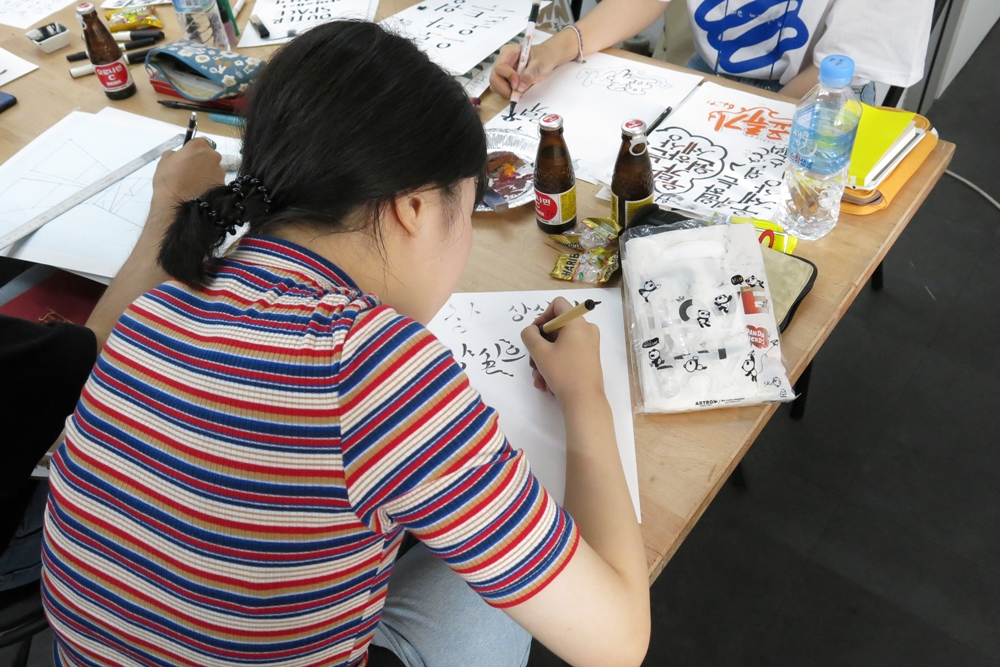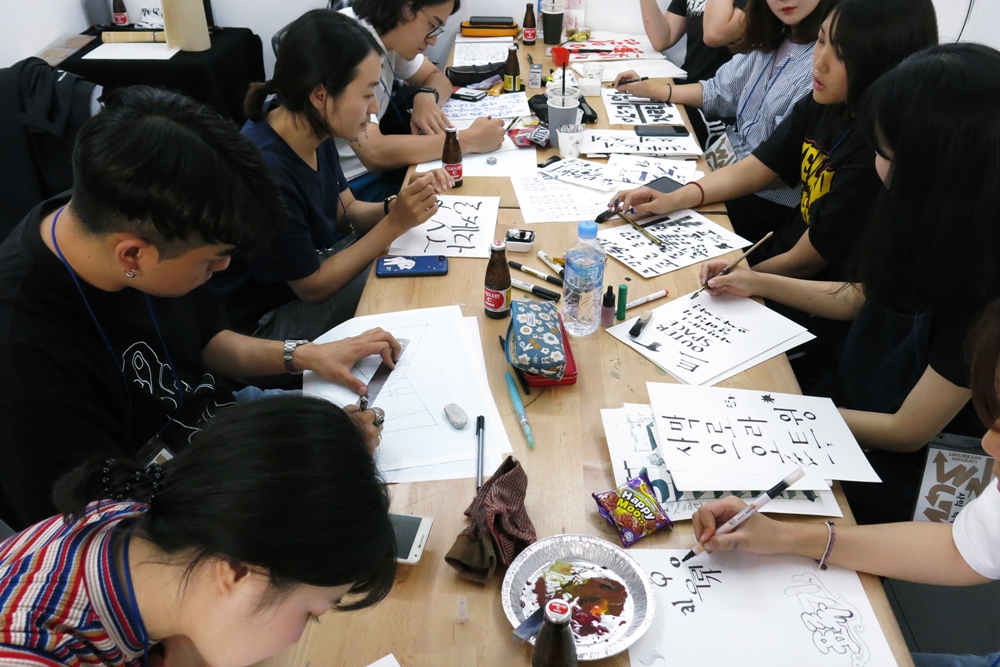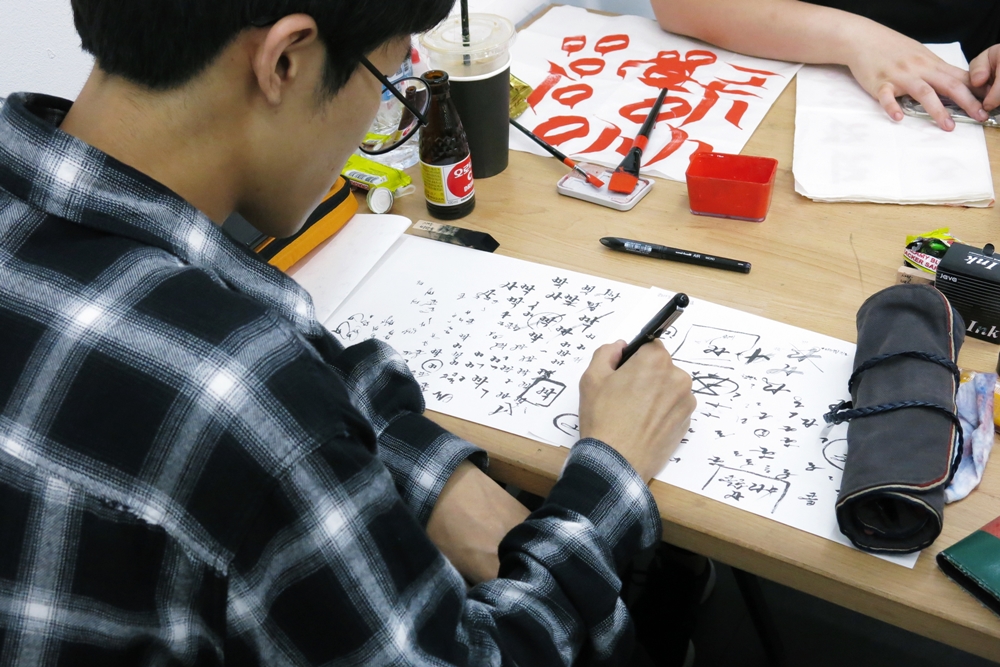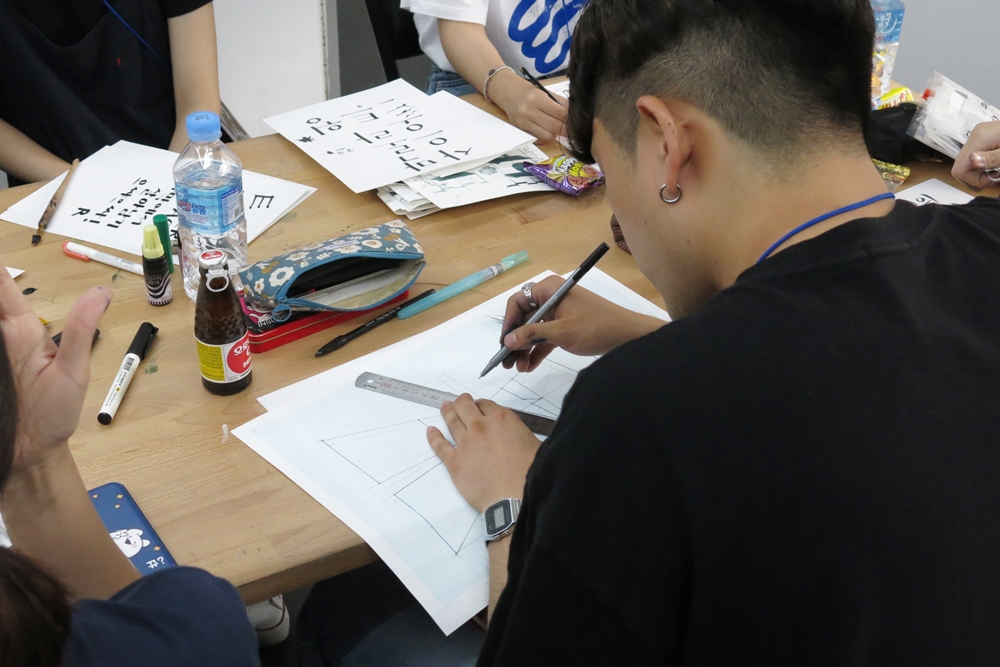
표류된 디자이너들의 탈출기, <디자인캠프2018, 우정국 표류기>를 다녀와서
<우정국 표류기>.
처음 캠프의 주제를 보았을 때, 의아했다. ‘우정국은 무엇이고 디자이너들이 왜 표류를 하지?’
태풍 솔릭이 서울에 상륙하던 날, 의문을 해소하기 위해 표류의 현장을 찾았다. 올해로 4회째 맞은 디자인학교의 디자인캠프는 8월 22일부터 26일까지 4박 5일 동안 진행되었다. 상수역과 광흥창역 중간에 위치한 캠프 장소는 길을 잘못 들어섰나 싶을 정도로 의외의 곳에 있었다. 주택가들 사이에 덩그러니 위치한 건물의 외관은 오래된 동주민센터 같았다.
알고 보니 디자인캠프가 열린 ‘탈영역 우정국’은 실제로 창전동 우체국이었던 장소를 탈바꿈한 곳이었다. 우정국은 우체국의 옛말이며, 업무공간으로 쓰이던 1층과 관사로 쓰이던 2층이 모두 새로운 문화공간으로 활용되고 있었다.
안으로 들어서자 6~7명 정도 모인 디자이너들이 노트북으로 작업을 하면서 열띤 토론을 하고 있었다. 이번 캠프에서는 ‘우정국 표류기’라는 주제에 맞춰 ‘도시’, ‘우주,’ ‘사막’, ‘정글’, ‘바다’ 총 5개의 가상 표류지가 설정되어 있어, 캠프 기간 동안 각각의 표류지를 탈출하기 위한 프로젝트가 진행되었다. 참가자들은 한 가지의 컨셉을 선택하여 멘토와 함께 작업하며, 표류된 것처럼 컴퓨터나 인터넷을 사용할 수 없는 환경에서 작업해야 했다. 제한 조건은 캠프의 마지막 날이 다가올수록 점점 완화되었다.
우정국을 찾았을 때 모든 팀이 진지하게 작업을 하고 있었는데 그 중, ‘척박한 사막에서의 레터링’이라는 주제로 작업하는 사막팀의 멘토, 멘티와 대화를 나눴다.
INTERVIEW1. 멘토
구모아 디자이너 (안그라픽스 타이포그래피 연구소 연구원)
디자인 캠프에 어떻게 참가하게 되셨나요?
디자인학교의 김의래 선생님 수업을 학생으로 들었던 게 인연이 되었어요. 각자의 자리에서 열심히 일을 하고 있었죠. 저는 폰트 디자인을 계속하고 있었는데, 선생님께서 디자인캠프에서 레터링 부분을 담당해 달라고 제안해주셔서 참여하게 되었어요.
사막팀 프로젝트는 어떤 컨셉을 갖고 있나요?
이번 디자인캠프 전체 컨셉이 ‘표류’에요. 그중에서 사막이라는 공간 컨셉을 받았어요. 요즘 디자인 작업은 거의 컴퓨터로 바로 시작을 하잖아요. 이번 프로젝트에서는 컴퓨터 작업 전에 손으로 직접 글씨도 써보고 서법도 배우고, 영문 캘리그래피도 경험해보는 시간을 가져요. 지금의 글자들이 형태를 갖추게 된 원리를 먼저 짚는 거예요. 그다음 개인마다 컨셉을 정해서 한 장의 레터링으로 보여줄 수 있게 커리큘럼을 짰어요. 지금은 한창 컨셉 만드는 중이에요.
멘티분들과 만나는 게 디자이너로서 작업하시는 데 어떤 의미가 있나요?
수업을 구상하면서 저도 많이 배우고 있고요. 멘티분들 만나서 새로움, 자유로움도 느끼고 에너지를 많이 받는 것 같아요. 폰트 디자인이라는 전문적인 분야만 하다가 원리를 다시 되짚어보니까 좋고요. 준비하면서 옛날에 했던 작업도 꺼내 보고 그랬어요.
멘토와의 상담시간 프로그램도 있던데, 어제도 상담하셨나요?
네. 두 분과 상담했어요. 아무래도 글자 디자이너를 보는 게 흔한 일이 아니라서 같은 팀이 아니더라도 글꼴에 관심 있는 분도 오셨어요. 그분들이 자기 작업물을 보여주면서 의견도 묻고 앞으로 글꼴 디자이너로 성장하고 싶은데, 어떤 과정이 필요한지 물어보시고 그랬어요.
레터링 작업을 하실 때 가장 중요하게 생각하시는 부분이 있나요?
레터링이 글자로 어떤 의도를 표현하는 거잖아요. 그래서 ‘의도’를 가장 중요하게 얘기하고 있어요. 어떤 것을 표현하고 싶은지, 어떤 글귀, 어떤 마음을 표현하고 싶은지 아는 게 중요하죠. 내가 표현하고 싶은 게 무엇인지를 문구로 직접 표현할 수도 있지만, 글자 형태에 녹여내서 표현할 수 있게 방향을 잡았어요. 개인적으로도 그렇게 하는 편인 것 같아요. 글꼴 디자인은 색깔을 너무 드러내지 않는 선에서 작업을 해야 하고, 레터링은 의도를 드러내는 게 훨씬 중요한 작업이죠.
INTERVIEW2. 멘티
박한솔 학생 (시각디자인 전공)
디자인캠프는 어떻게 알고 참가하셨나요?
친구가 이번에 디자인캠프 포스터 워크숍에 참여해서 사막 포스터를 만들었어요. 그 덕에 캠프를알게 되었고 추천해줘서 참가하게 되었어요. 평소에 레터링하고 폰트에도 관심이 많았고요. 처음 참가하는 건데 재미있어요.
무엇이 가장 좋았나요?
아무래도 다양한 분들을 만날 수 있다는 게 좋아요. 학생들도 있고, 회사에서 디자인하시는 분들도 있고, 디자인 분야도 다양하다 보니 모두 한자리에서 모여서 대화할 수 있다는 것이 장점이에요.
팀으로 작업하는 게 도움이 되었나요?
도움이 돼요. 학교 다닐 때 보다 분위기가 벽이 없다고 해야 할까요? 다른 팀 사람에게도 편하게 다가갈 수 있어서 아이디어도 얻을 수 있고요. 교류할 수 있어 좋은 것 같아요.
폰트에 관심을 두게 된 계기가 있나요?
처음 시작은 ‘바람체’를 보고 멋있어서 관심을 갖게 되었어요. 그 이후로, 학원에서 폰트를 배우고 흥미로 시작하게 되었는데 잘 맞아서 지금까지 해보고 있어요.
캠프 기간 동안 아쉬웠던 부분이 있나요?
한가지 수업만 듣는 게 조금 아쉬워요. 물론, 시간적인 제약이 있다는 것은 이해하지만요. 레터링뿐만 아니라 포스터 만드는 작업까지 다 같이 해보고 싶은데 신청한 한 가지만 할 수 있어서 아쉬웠어요.
열의가 넘치는 참가자의 인터뷰를 마치고 나니, 디자인캠프의 시작이 궁금해졌다. 마침 디자인학교의 이지원 교수를 만나 물어볼 수 있었다.
“우리가 일만 하다 보면, 일의 의미를 잃기가 쉬워요. 이런 상황에서 돌파구는 사람 관계라고 생각했어요. 비슷한 고민을 하는 사람들을 만나는 거죠. 디자이너들끼리의 모임을 만들고 싶어서 캠프를 시작하게 되었어요. 그리고 두 가지를 유지하기 위해서 노력했습니다. 첫째, 열망 있는 사람들이 모이는 것. 둘째, 캠프를 오래 지속해 나가는 것. 이것이 지켜졌기 때문에 지금까지 온 것 같아요.”
일하면서 겪는 어려움을 함께 나누고 공감할 수 있는 것, 해결책을 찾고 새로운 자극을 받으려는 열정적인 동료를 만날 수 있는 것이 디자인학교 디자인캠프만의 큰 장점이라고 할 수 있다.
디자인학교는 캠프에서 이뤄지는 강연자와 멘토를 섭외할 때 다른 무엇보다 교육자로서 가치 있는 생각과 판단을 갖춘 사람을 섭외하려고 애쓴다고 한다. 참다운 ‘교육’의 본질에 최선을 다하는 우직한 노력이 사람들에게 진정성 있게 다가왔기 때문에 지금의 디자인캠프가 있는 것 아닐까? 따뜻한 디자이너 공동체를 지향하는 디자인학교의 디자인캠프가 계속해서 사랑받을 수 있기를 바라본다.